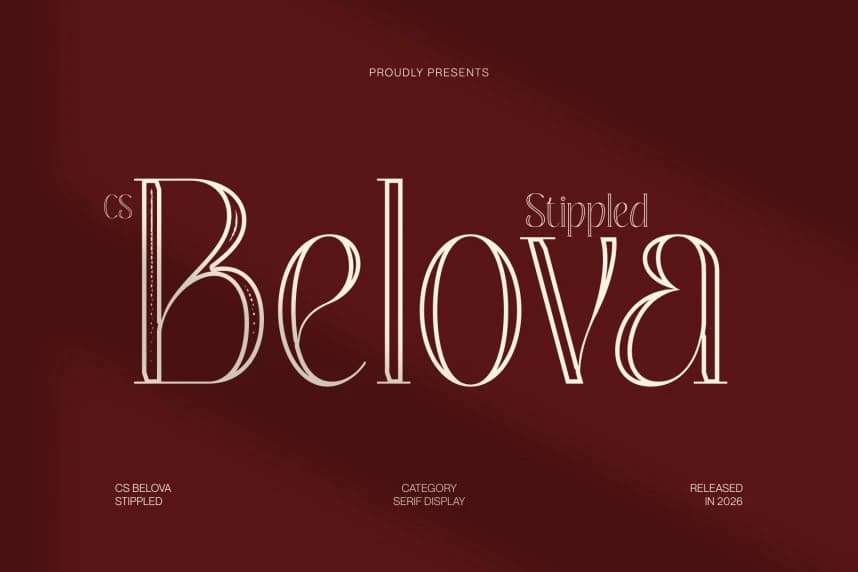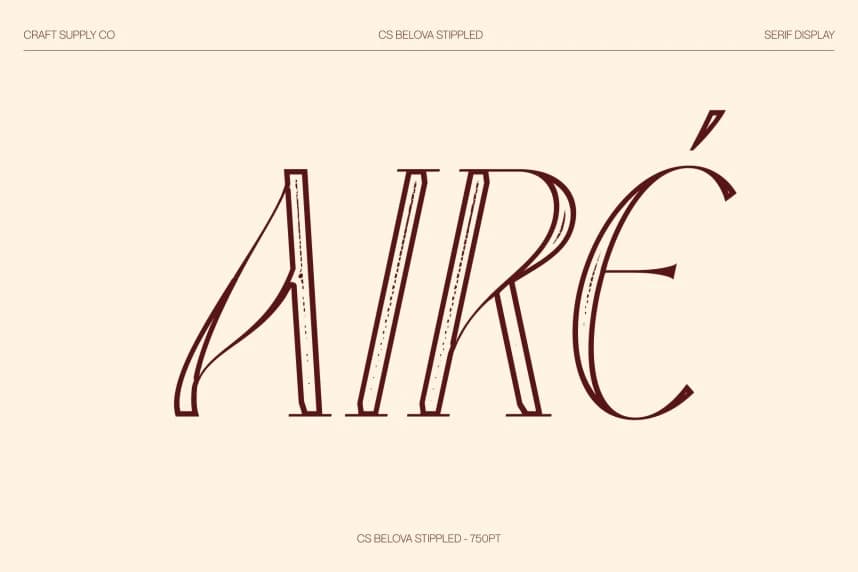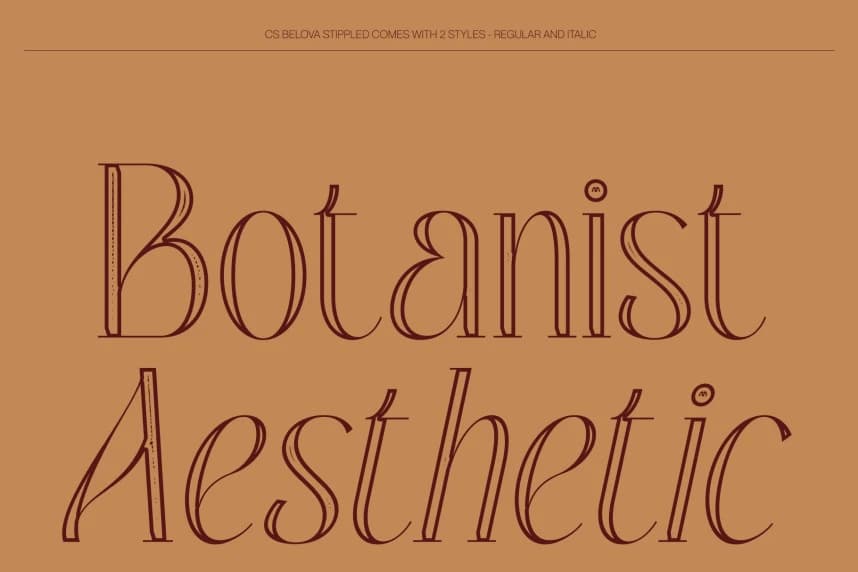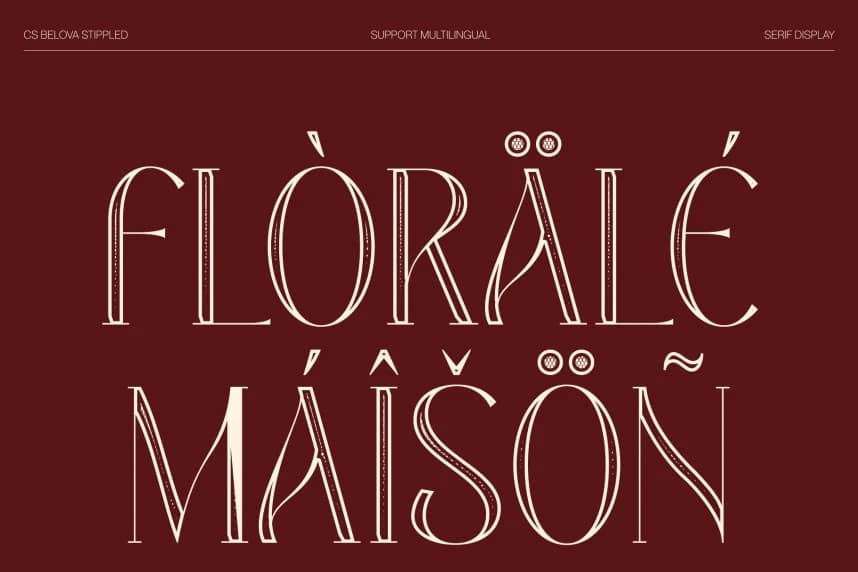
CS Belova Stippled Font
CS Belova Stippled Font – Oyunbaz bir modern güzellik ile zarif bir serif. İnce zarafet, stippled detayla birleşir. Bu, temiz, ince çizgilerle özenle tasarlanmış ve zarif stippled dokusuyla zenginleştirilmiş bir serif fontudur.
CS Belova Stippled Font – Zarif Serif, Oyunbaz Modern Güzellik ile İnce Zarafet; Noktalı Detayla. Bu zarif serif yazı tipi temiz, ince hatlarla üretilmiş ve zarif noktalı dokusu ile zenginleştirilmiştir.
CS Belova Stippled
CS Belova Stippled Regular